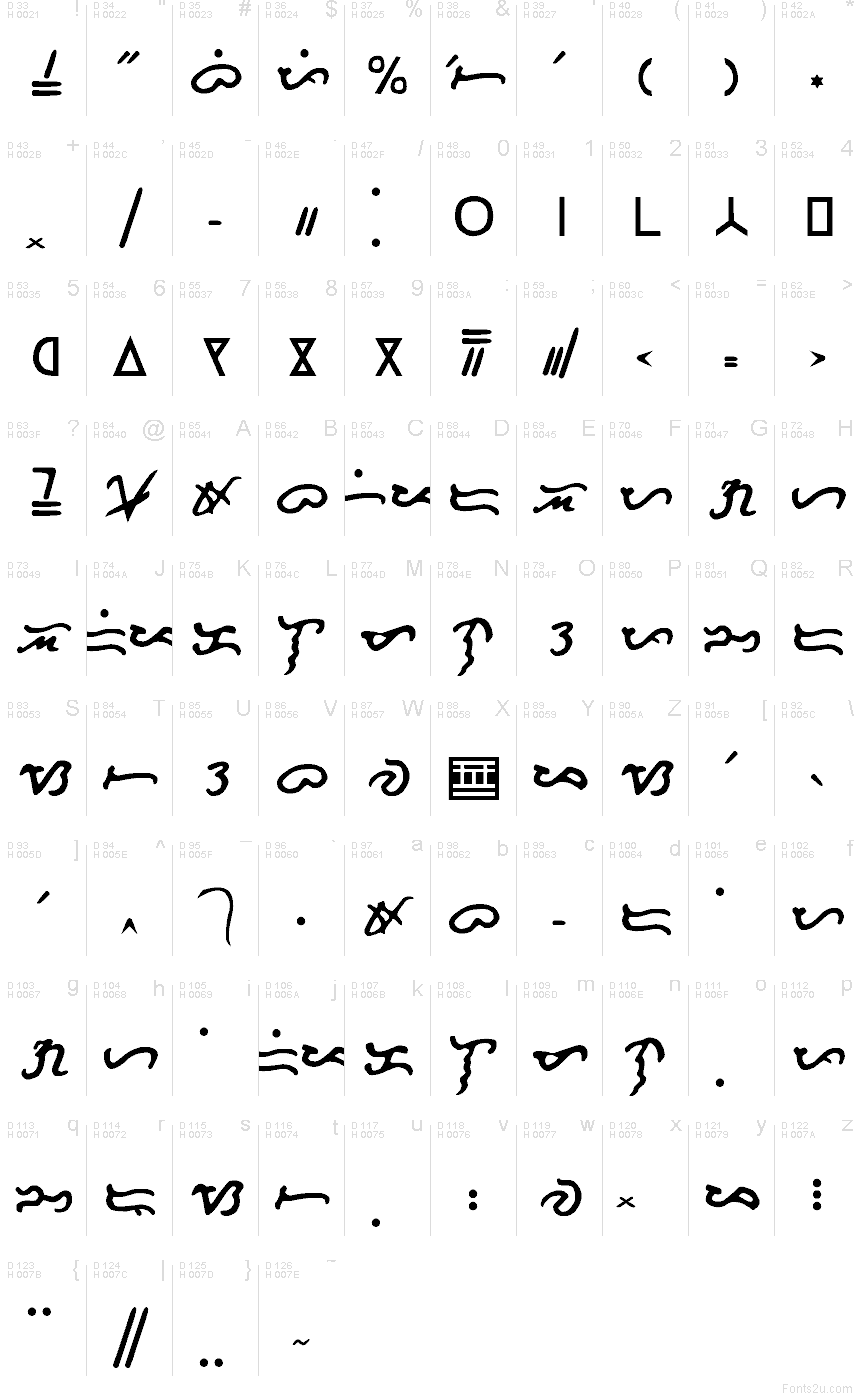
GAT RISAL
Gat Risal od Apulakan Siklab je bezplatné abstraktní kaligrafické písmo dingbat, které je postaveno z rozmanitých černých tvarů. Jeho symboly kombinují široké tahy připomínající štětec, utažené smyčky, dlouhé háčky a občasné vodorovné pruhy a vytvářejí značky, které připomínají vymyšlené písmo.
Experimentální módní značka nebo hudební vydavatelství by mohly tyto tvary využít pro branding, merchandise a plakáty na akce. Symboly připomínající logo jsou jeho nejpřesvědčivější rolí, protože každý znak působí spíše jako obrázek než jako obyčejný text.